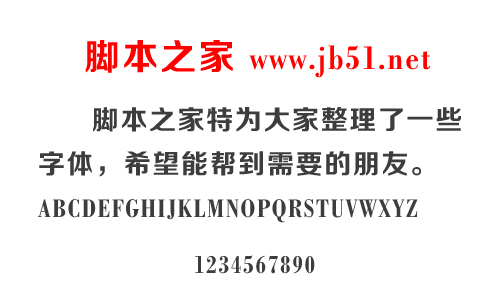
碳纖維正粗黑簡(jiǎn)體字體是碳纖維字庫(kù)推出的一款粗黑字體,該字體是在黑體字體的基礎(chǔ)上設(shè)計(jì)而來(lái)的,在保留黑體特點(diǎn)的同時(shí)又做了一些創(chuàng)新,更加時(shí)尚和實(shí)用,字體結(jié)體疏朗簡(jiǎn)潔、工整端莊,筆觸圓潤(rùn)、粗細(xì)均勻,風(fēng)格簡(jiǎn)約流暢、剛?cè)岵?jì)??梢赃m用于名片設(shè)計(jì)、平面設(shè)計(jì)、廣告設(shè)計(jì)、報(bào)紙雜志、企業(yè)LOGO、商標(biāo)注冊(cè)、電視臺(tái)廣告等領(lǐng)域!歡迎需要的朋友前來(lái)下載。
碳纖維正粗黑簡(jiǎn)體字體